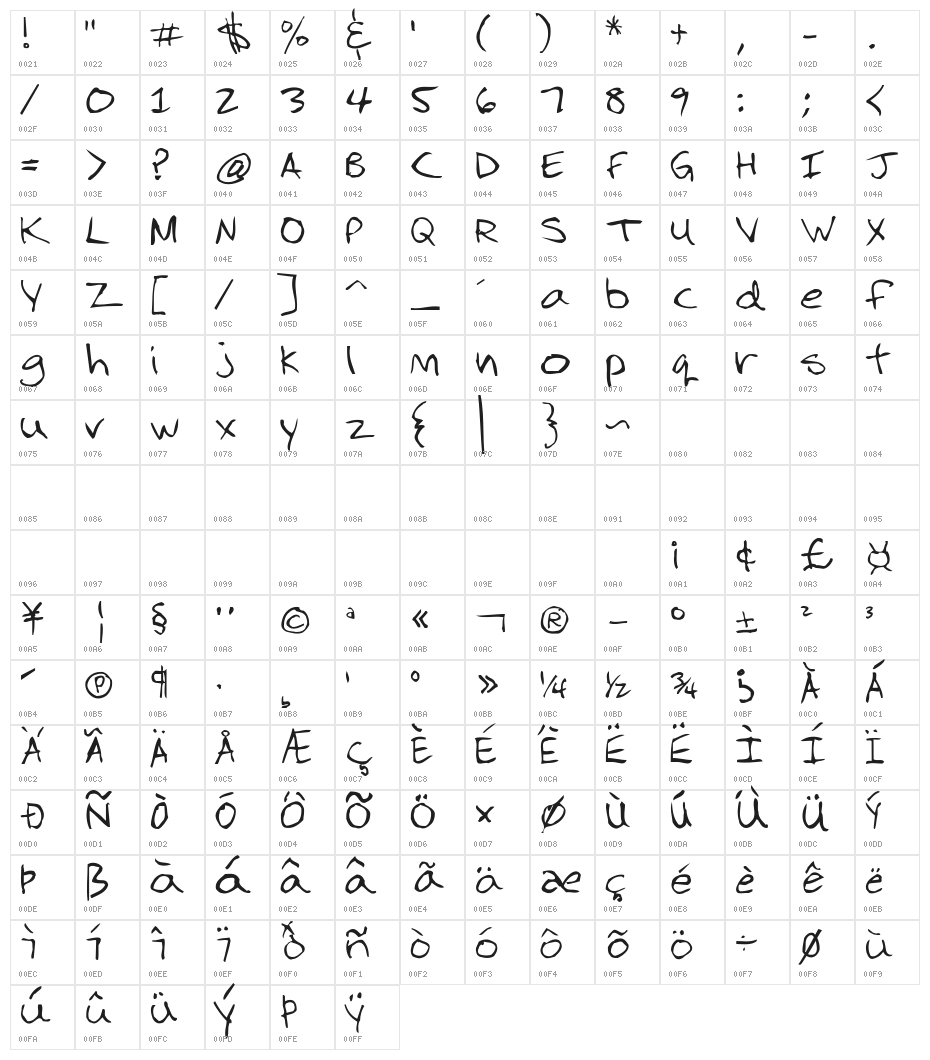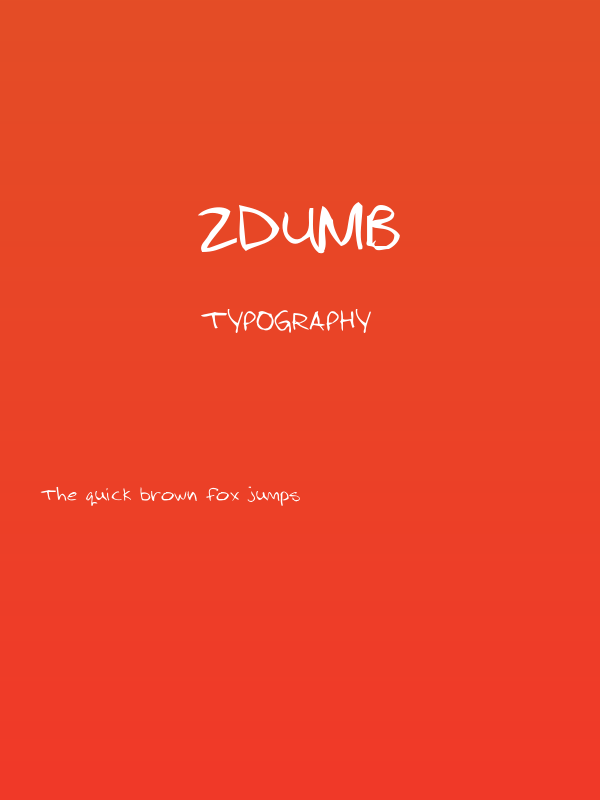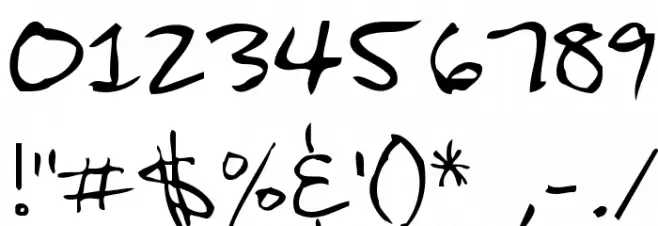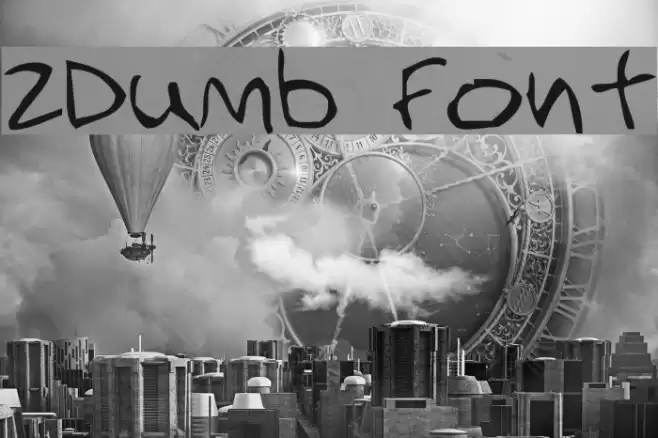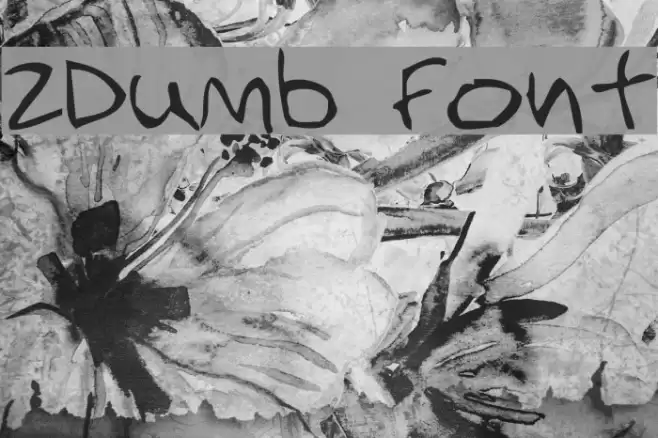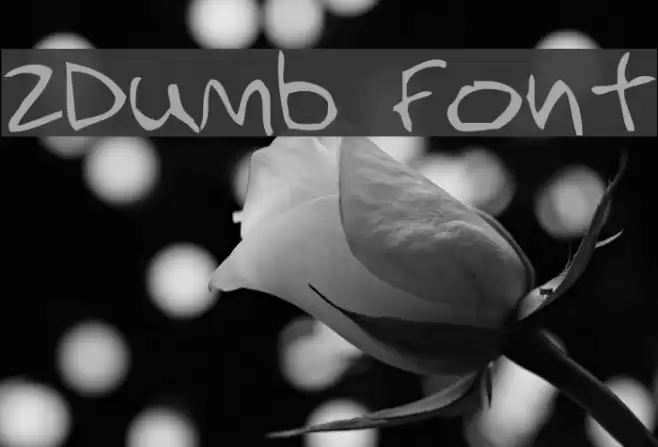
2Dumb Font
✎ Handwritten
| श्रेणियाँ | Handwritten |
| समग्र शैली | Decorative |
| उपयोग का मामला | Logos, Headlines, Informal Text |
| सुझाए गए प्रोजेक्ट | Ideal for greeting cards, children's books, playful branding, and creative posters. |